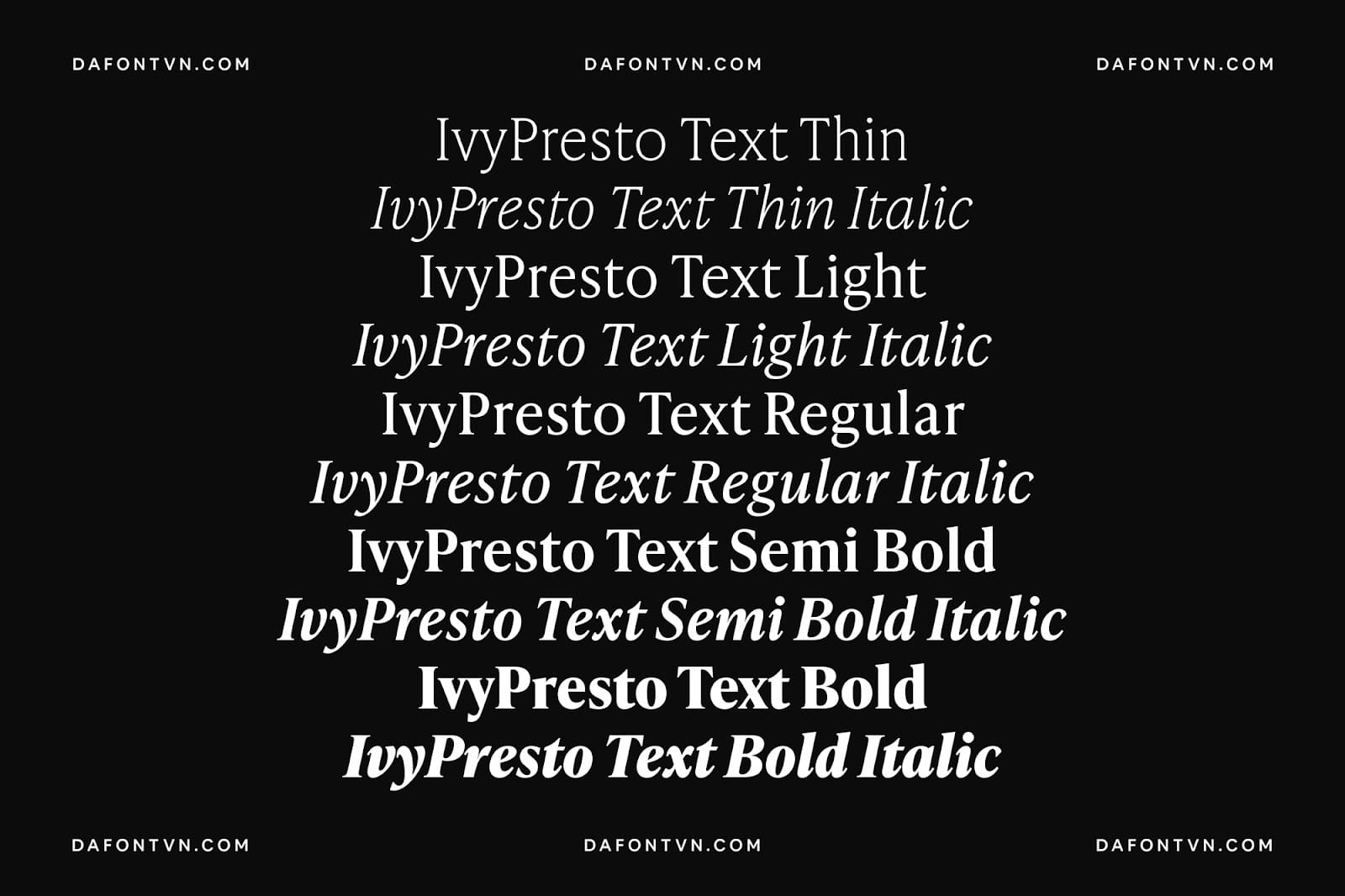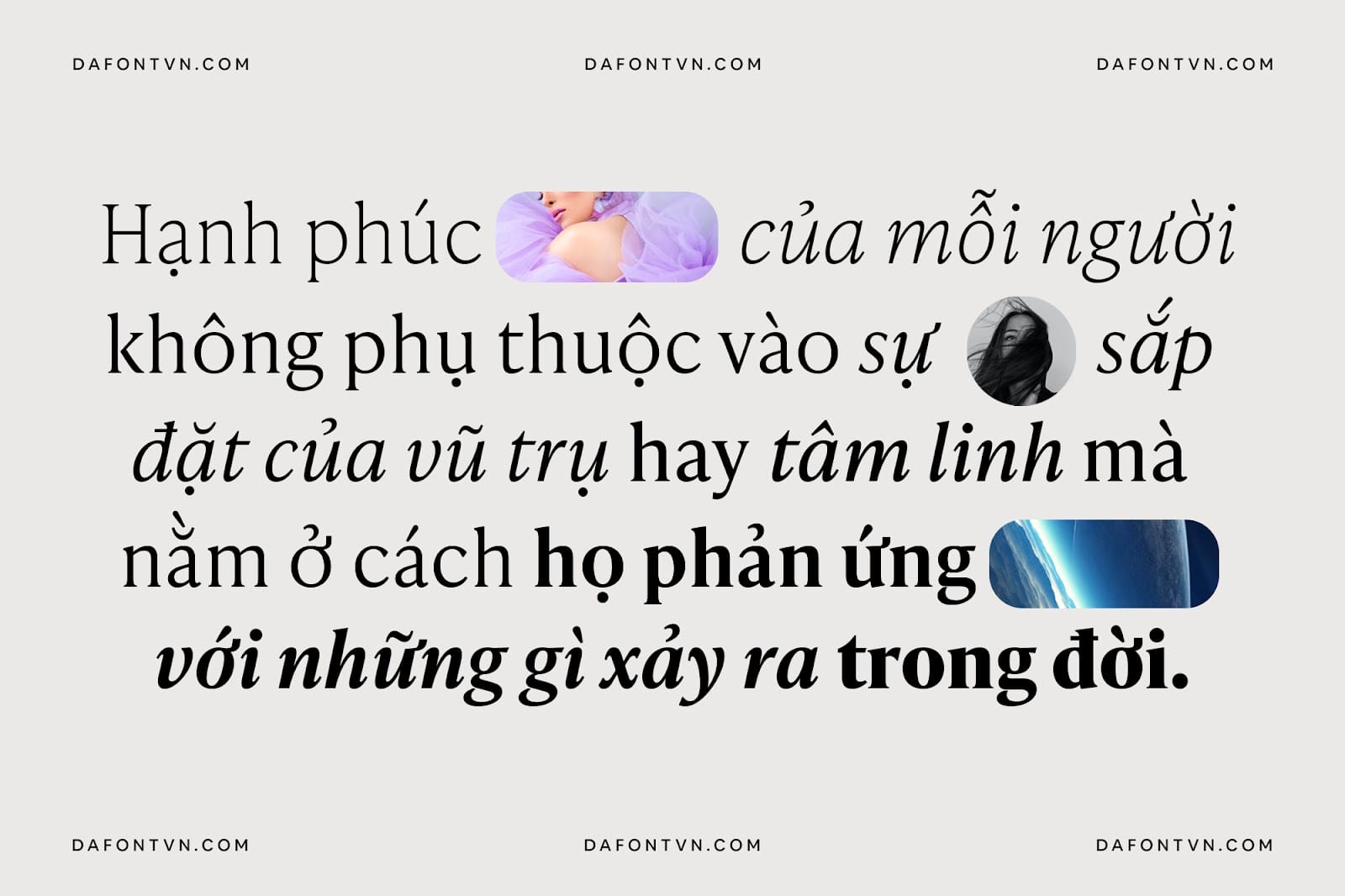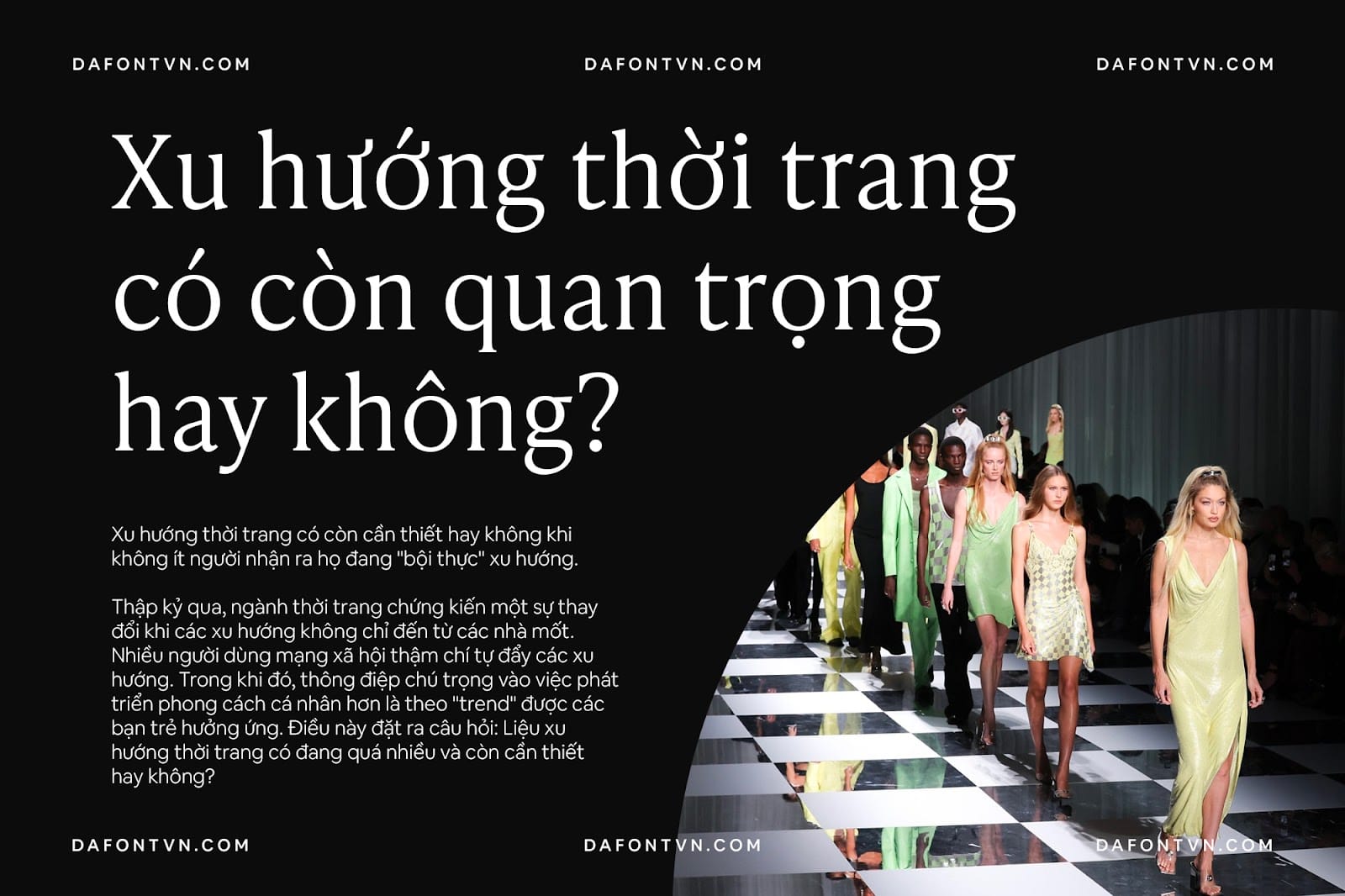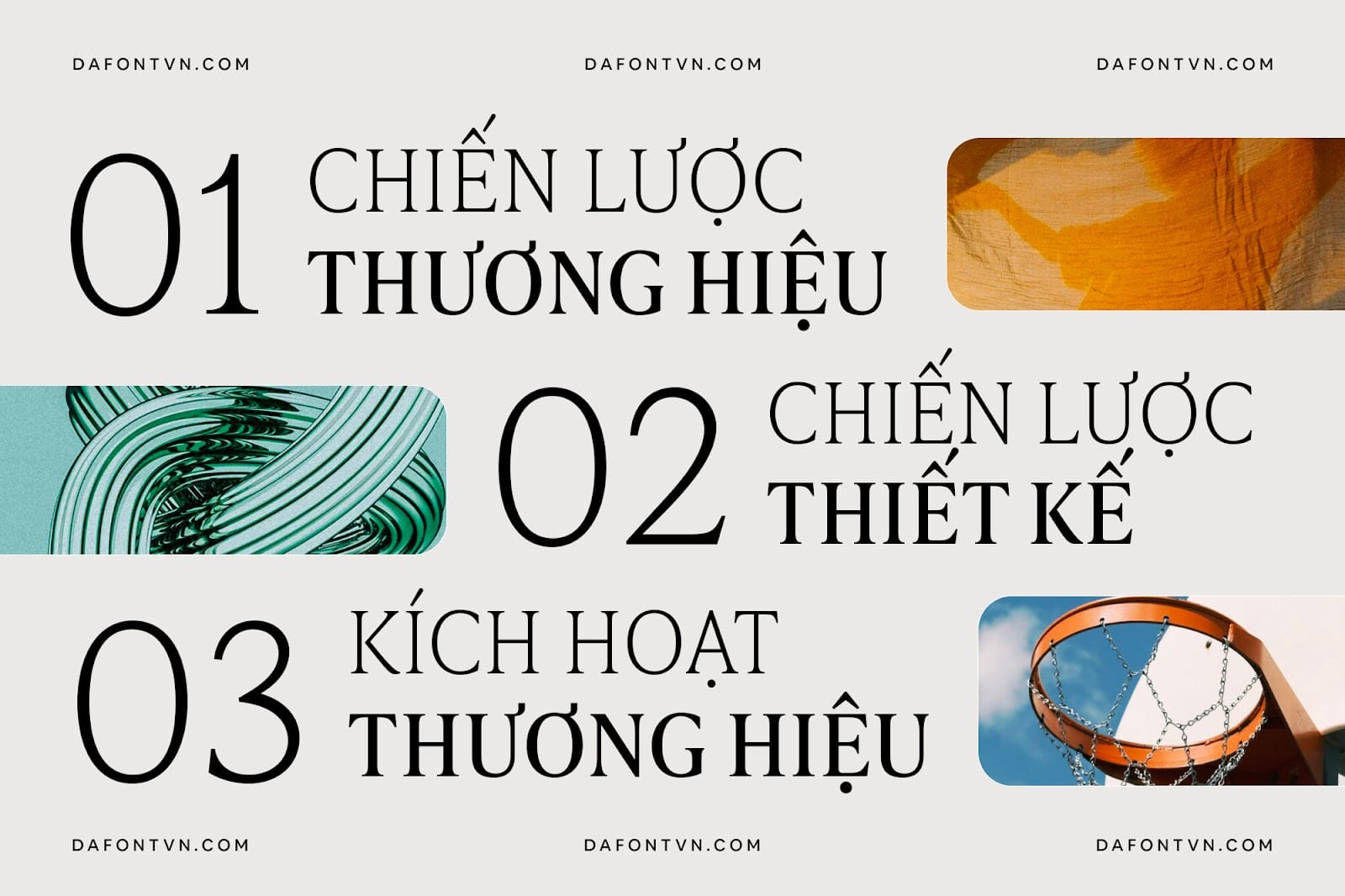
Trọn bộ font IvyPresto Text Việt hóa (10 font)
IvyPresto là một kiểu chữ serif được thiết kế bởi Jan Maack. Bộ font chữ này được lấy cảm hứng từ tác phẩm của nhà thiết kế khuôn mẫu Hendrik van den Keere thế kỷ thứ mười sáu. Bộ font chữ IvyPresto bao gồm — IvyPresto Text, IvyPresto Headline và IvyPresto Display, mỗi kích thước có 5 trọng lượng và kiểu nghiêng tương ứng.
Đây là bộ font IvyPresto Text Việt hóa đầy đủ 10 kiểu. Bộ font được thiết kế với chiều cao x lớn, nét chữ mỏng, đường nét mỏng và tỷ lệ hẹp khiến IvyPresto trở nên lý tưởng cho việc sử dụng kiểu chữ hiển thị.
Bộ font phù hợp cho rất nhiều thiết kế như xây dựng thương hiệu, bố cục website, tiêu đề, tiêu đề tạp chí, sản phẩm, thời trang, điện ảnh, quảng cáo, thiệp mời…